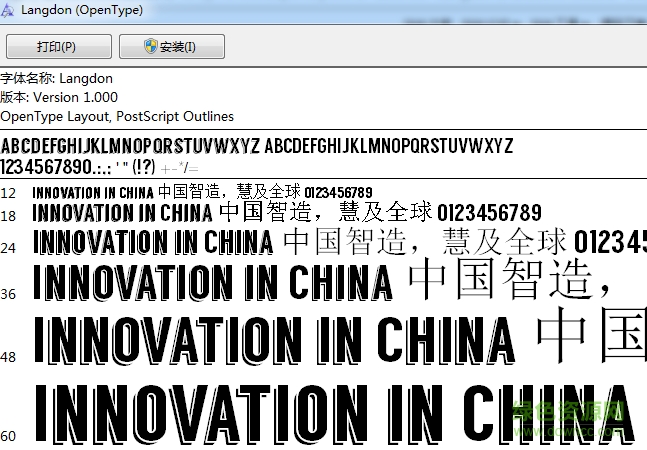
Langdon字體是一款超好用的英文字體,這款字體由XLN Telecom(XLN電信) 與頂尖領(lǐng)先設(shè)計(jì)師、插畫(huà)師以及字體設(shè)計(jì)師 Steven Bonner 共同完成。一款認(rèn)真值得信賴(lài)的字體。有喜歡這款字體的朋友就趕快來(lái)綠色資源網(wǎng)下載使用吧!
Langdon字體是一款英文字體,字體的線(xiàn)條效果十分出色,讓用戶(hù)能夠享受設(shè)計(jì)帶來(lái)的好處,有需要的朋友就趕快來(lái)綠色資源網(wǎng)下載吧!